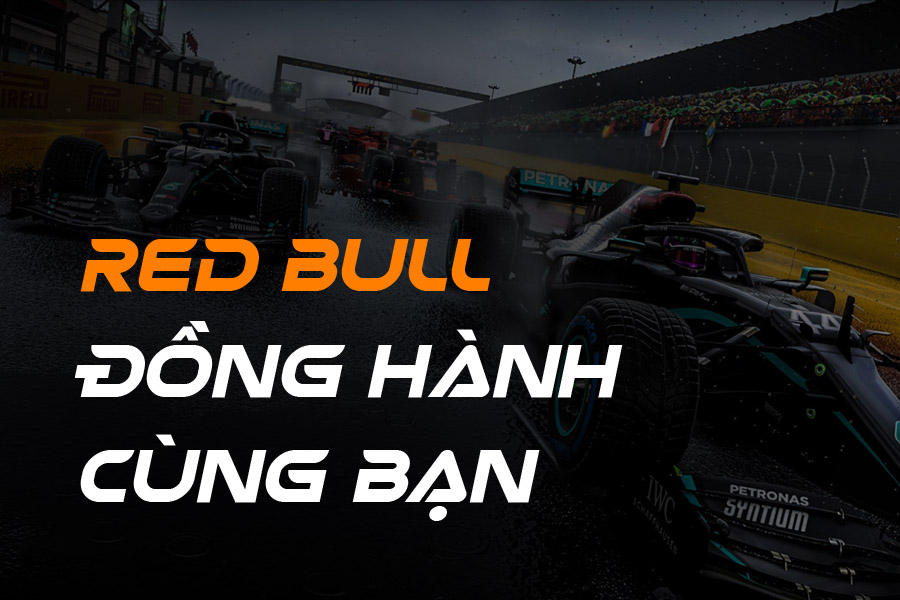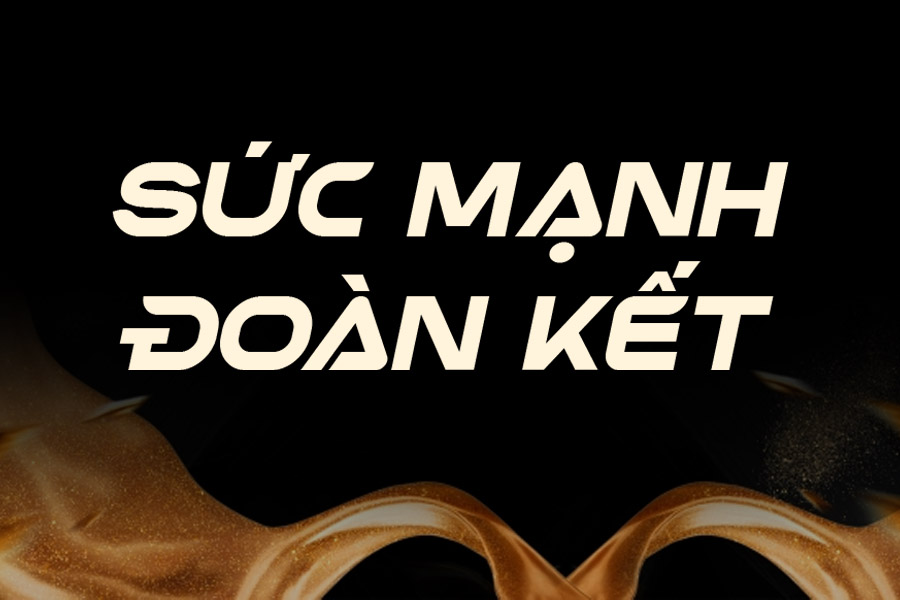
Font chữ thể thao mang phong cách tương lai TH Geardive
Trong thế giới thiết kế đồ họa hiện đại, đặc biệt là lĩnh vực branding cho các giải đấu, đội tuyển e-sports hay ấn phẩm quảng cáo xe hơi, việc tìm kiếm một font chữ thể thao ưng ý luôn là ưu tiên hàng đầu của các Designer. Để đáp ứng nhu cầu đó, hôm nay chúng tôi xin giới thiệu bộ phông chữ TH Geardive – một phiên bản font chữ Việt hóa đầy ấn tượng được thực hiện bởi Team TH, dựa trên nguyên bản Geardive nổi tiếng của tác giả Ben Type.
Đặc điểm nổi bật của TH Geardive
Geardive gốc được cộng đồng thiết kế quốc tế đánh giá cao nhờ phong cách Futuristic (Tương lai) kết hợp với sự mạnh mẽ của Sporty (Thể thao). Khi nhìn vào TH Geardive, bạn sẽ thấy ngay tinh thần của sự chuyển động không ngừng. Với cấu trúc nghiêng đặc trưng cùng những đường cắt sắc bén, dứt khoát, đây chính xác là một font chữ tốc độ dành cho những thiết kế cần sự bứt phá và năng lượng bùng nổ.
Các ký tự trong bộ font này được thiết kế với độ dày đồng đều, tạo cảm giác chắc chắn, tin cậy nhưng không hề thô cứng. Sự cân bằng giữa các khoảng âm và dương trong con chữ giúp TH Geardive hiển thị tốt ngay cả ở kích thước lớn trên các banner quảng cáo ngoài trời hay trên các ấn phẩm kỹ thuật số.
Font TH Geardive Việt hóa: Tuyệt phẩm Font chữ thể thao mang phong cách tương lai
Tại sao nên sử dụng phiên bản Việt hóa từ Team TH?
Một trong những trở ngại lớn nhất khi sử dụng các font chữ nước ngoài là vấn đề gõ tiếng Việt. Hiểu được điều này, đơn vị thực hiện là Team TH đã tiến hành Việt hóa bộ phông này một cách vô cùng tỉ mỉ. Các dấu tiếng Việt được vẽ mới và cân chỉnh kerning kỹ lưỡng để đảm bảo sự hài hòa, không phá vỡ cấu trúc hình học độc đáo của bản gốc.
Nếu bạn là người thường xuyên sưu tầm và sử dụng các bộ font th (các font được Việt hóa bởi Team TH), bạn sẽ nhận thấy chất lượng hoàn thiện của TH Geardive rất cao. Font chữ này cực kỳ thích hợp để làm tiêu đề (headline), logo thương hiệu, số áo thi đấu hoặc các poster phim hành động.
TH Geardive là sự kết hợp hoàn hảo giữa thẩm mỹ hiện đại và tính ứng dụng cao cho người dùng Việt. Hy vọng bộ font chữ Việt hóa này sẽ là nguồn cảm hứng mới mẻ, giúp các dự án thiết kế của bạn trở nên chuyên nghiệp và cuốn hút hơn.
Font TH Geardive Việt hóa: Tuyệt phẩm Font chữ thể thao mang phong cách tương lai